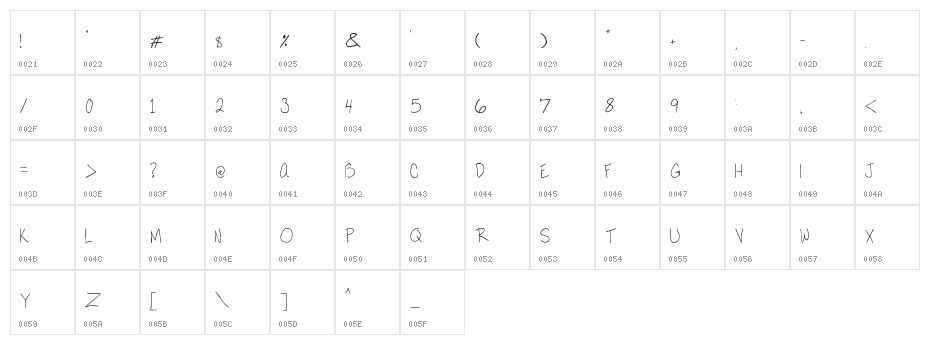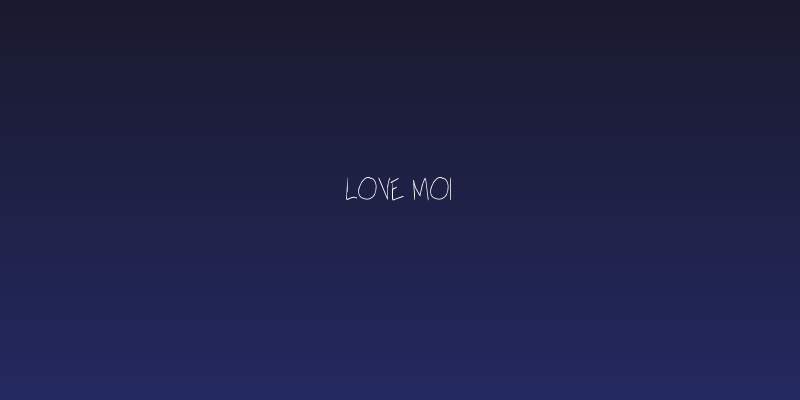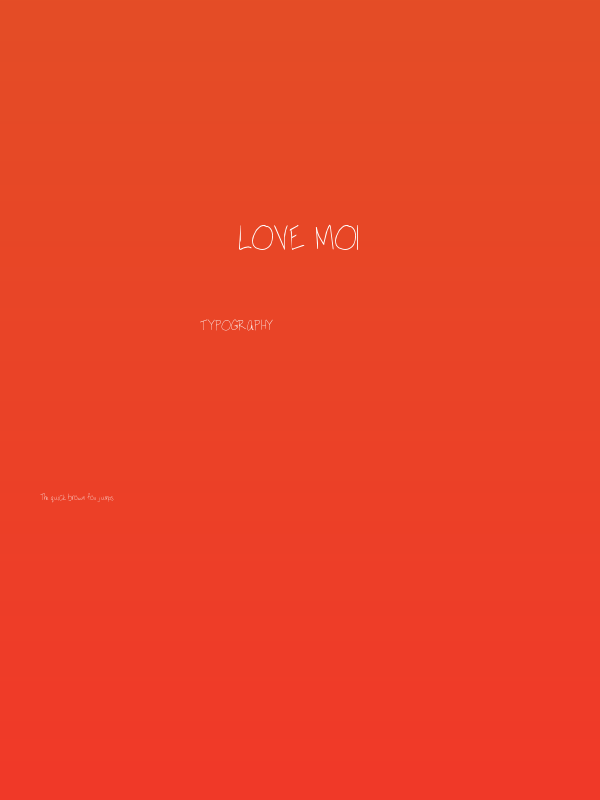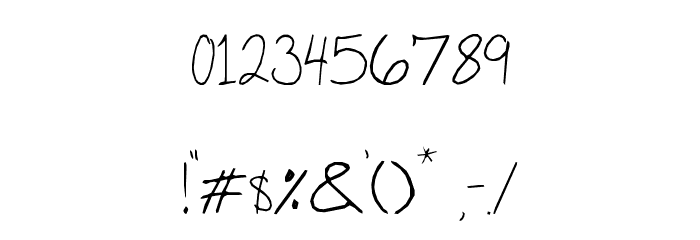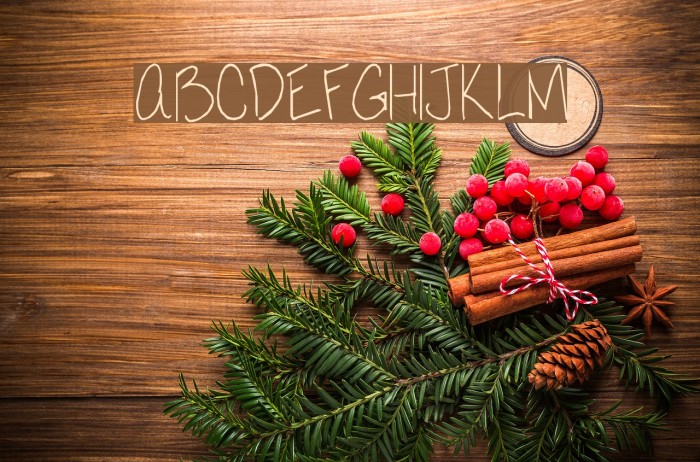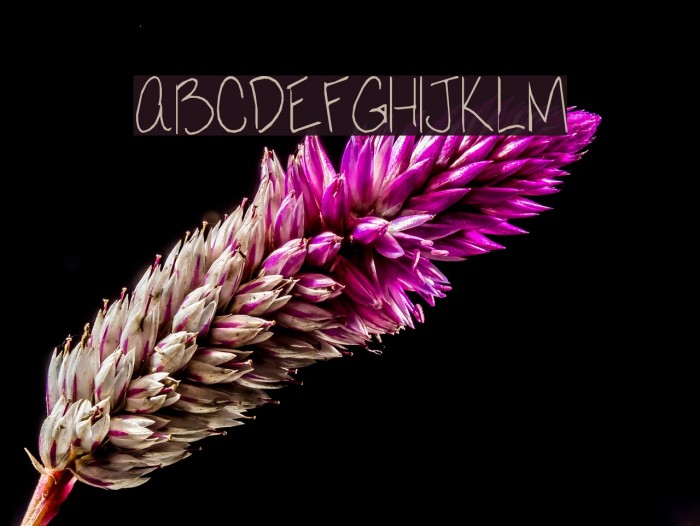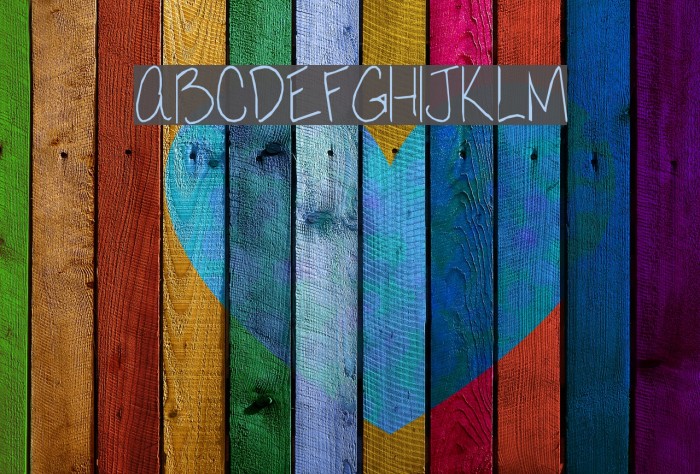
Love Moi Font
| Caz de utilizare | Headlines, Logos, Invitations |
| Proiecte propuse | Ideal for greeting cards, invitations, children's books, and personal branding projects. |